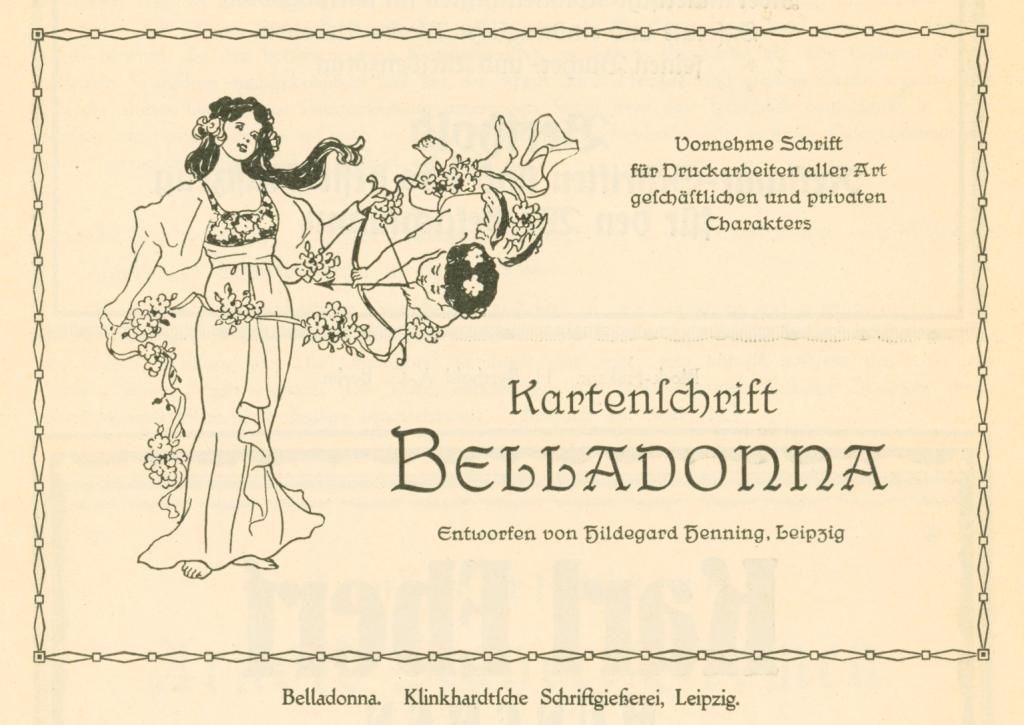
#59 mulheres na tipografia: uma breve linha do tempo
ou "precisamos rever nossas narrativas" | tempo de leitura: 7 minutos
Bodoni, Garamond, Baskerville e Caslon. talvez você não saiba o rosto dessas pessoas, mas deve saber (ou pelo menos supor) que são todos homens. homens que emprestaram seus nomes para batizar algumas das mais importantes famílias tipográficas até hoje. alguém pode alegar que eram outros tempos - daí a ausência de mulheres, certo? mas mesmo no século XX (quando dar seu próprio nome a uma fonte saiu de moda) as criações mais celebradas - como a futura, a times new roman, a helvetica - também são assinadas por homens. esse visão - um pouco superficial, admito - me fez chegar a uma conclusão falaciosa: a de que mulheres haviam se envolvido no ofício tipográfico muito tarde, e era por isso que eu não conhecia seus nomes. mas eu estava errada, e fiquei muito feliz quando percebi isso.
📜 O que você sabe sobre a história das mulheres na tipografia?
O que eu soube, por muito tempo, se resumiu ao fato de que elas não figuram entre os tipógrafos mais lembrados da história do design. Depois, descobri que foram consideradas “inimigas naturais dos livros” tanto quanto os ratos ou a poeira.
Com isso na cabeça, eu naturalizei a ideia de que a participação feminina na tipografia havia sido adiada tanto quanto possível, e que era por isso que eu conhecia tão poucos nomes de mulheres tipógrafas, especialmente na era dos tipos metálicos. Mas apesar disso, há alguns meses eu decidi reunir alguns textos sobre a história das mulheres tipógrafas, uma pequena bibliografia para consultar quando precisasse. Foi quando digitei despretensiosamente “first female typographer” no Google e ... esse título é de Anna Rügerin, que viveu no século XV.
Descobri que há mulheres envolvidas nos ofícios relacionados à tipografia desde muito cedo, incluindo a produção de livros, encadernação, impressão e até a fundição de tipos metálicos. Por isso decidi compilar nessa edição uma breve linha do tempo. Não se trata de uma narrativa realmente linear e muito menos uma sequência definitiva ou completa dos fatos, mas é pelo menos uma longa lista de mulheres de quem pouco se fala, organizada de maneira cronológica. Ao contar um pouco sobre cada uma delas, espero estar combatendo de alguma forma o seu apagamento histórico.
⏳ Breve linha do tempo sobre a atuação feminina na tipografia, de 1481 a 1937
1481/82: Primeiro registro de uma mulher atuando na composição de um livro, uma freira. Não consegui encontrar seu nome, mas de acordo com este artigo do blog I Love Typography, o livro de registros do convento foi encontrado no século XVIII e confirma que ela trabalhou em uma edição de Il Morgante, obra do poeta italiano Luigi Pulci, na editora do convento em que vivia e trabalhava em Florença.
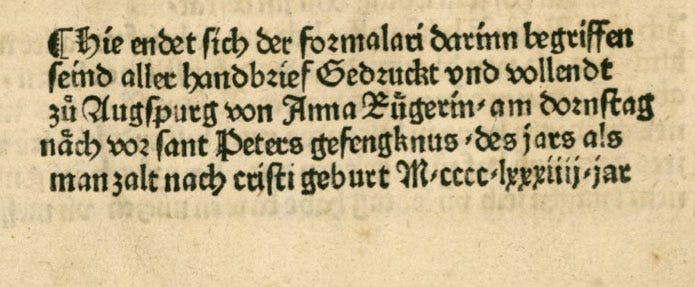
1484: Anna Rügerin é a primeira tipógrafa a incluir seu nome no Colofón de um livro, menos de três décadas depois da invenção da prensa móvel por Gutemberg. O nome de Anna consta nos títulos Sachsenspiegel, uma obra de prosa, e Formulare und deutsch rhetorica, um manual de edição para documentos e cartas. Para ambos os trabalhos ela usou uma fonte gótica criada por Johann Schönsperger, que a pesquisadora Sheila Edmunds acredita ser seu irmão. Aliás, esse é um ponto a ser observado: muitas das mulheres que puderam trabalhar como tipógrafas tinham pais, irmãos ou maridos envolvidos na área. Isso acontecia porque viúvas de impressores costumavam ter permissão para continuar a administrar o negócio dos falecidos para sustentar os filhos1.
[Glossário] Colofón ou colofão é a nota final de um manuscrito ou de um livro impresso, na qual normalmente constam informações sobre a publicação como o nome do autor do livro, o título da obra, o nome do impressor e/ou do editor e o lugar e a data da impressão.
1575: Katharina Gerlachin assume a editora de seu marido após sua morte e publica diversos títulos usando o próprio nome. Sua editora se tornou muito conhecida pelo pioneirismo na publicação de livros de música.
1638: Elizabeth Glover leva a primeira prensa móvel para as Trezes Colônias, a segunda da América do Norte (a primeira estava em Vera Cruz, no México). Ela inaugura uma editora passa a imprimir almanaques, jornais, etc. Após sua morte, a prensa é doada para a Universidade de Harvard, dando início ao que viria ser uma dia a Harvard University Press.
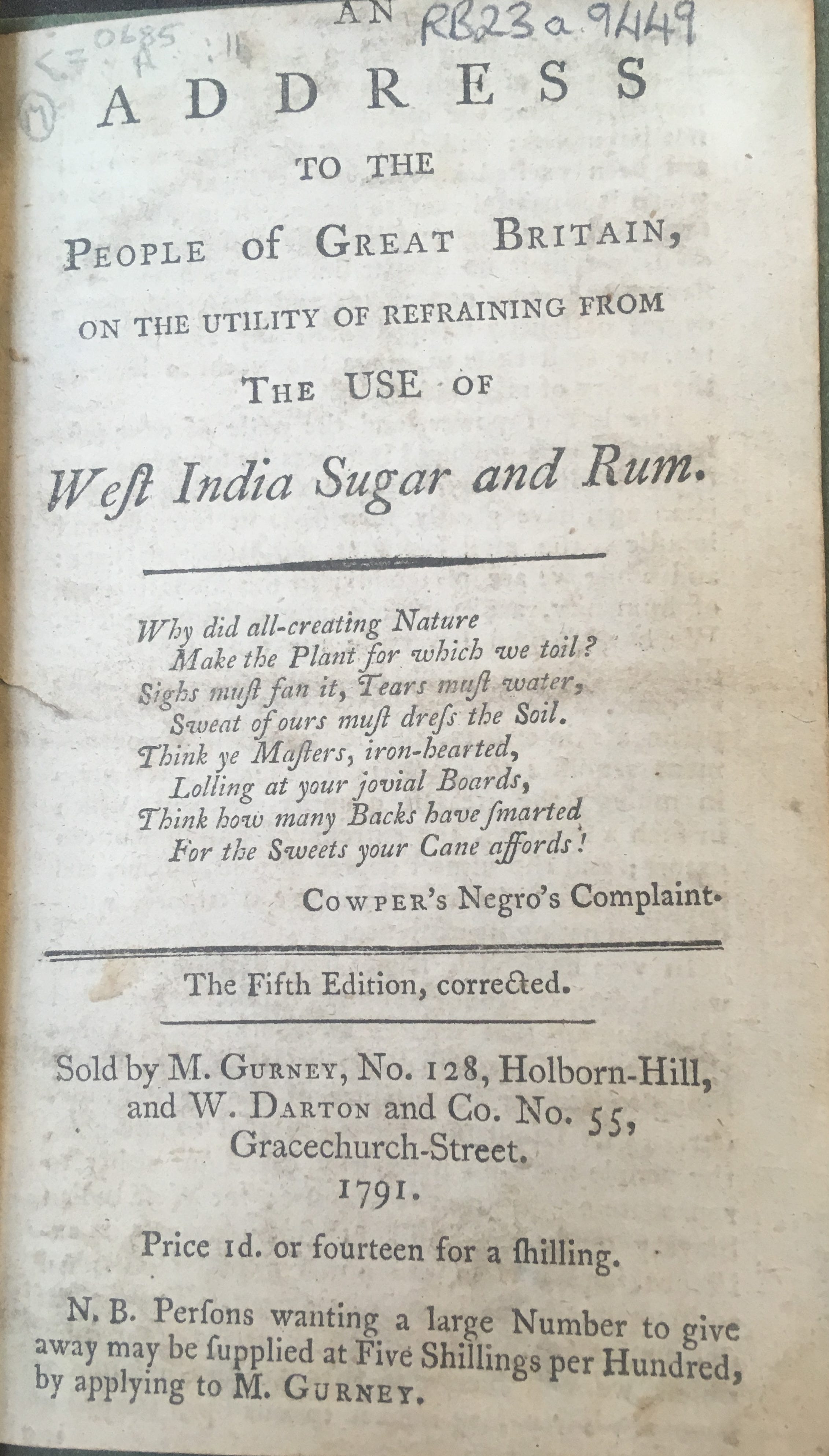
1791: Martha Gurney imprime e vende o panfleto mais amplamente distribuído da história até então. Martha era editora, comerciante de livros e uma ativista abolicionista. Estima-se que tenham sido produzidas de 100 a 200 mil cópias do panfleto An Address to the People of Great Britain, on the Propriety of Abstaining from West India Sugar and Rum, escrito por William Fox.
[Glossário] Um panfleto, historicamente, pode ser uma publicação de até 48 páginas em qualquer temática, de propaganda a discursos políticos - e não só aquele papelzinho que se pega na rua e joga fora.
1860: Emily Faithfull funda a Victoria Press, uma editora que empregava outras mulheres e publicava primariamente jornais, panfletos e revistas feministas. Um dos títulos, a Victoria Magazine, foi publicada mensalmente ao longo de 18 anos.
1912: Hildegard Henning é a primeira designer de tipos sobre a qual temos conhecimento - ou pelo menos a primeira a assinar uma fonte. Ela criou a Belladonna para a fundição Julius Klinkhardt, provavelmente como “freelancer”, já que não era funcionária da empresa.
1930: Beatrice Warde profere o discurso Printing should be invisible, também conhecido como A Taça de Cristal, na Guilda dos Tipógrafos Britânicos. O discurso sobre como a boa tipografia deve ser invisível foi publicado diversas vezes desde então e hoje, quase 100 anos depois, é considerado um cânone do design gráfico. Antes de chegar ao cargo de gerente de publicidade na Monotype, Beatrice publicou diversos artigos sobre tipografia sob um pseudônimo masculino, Paul Beaujon.